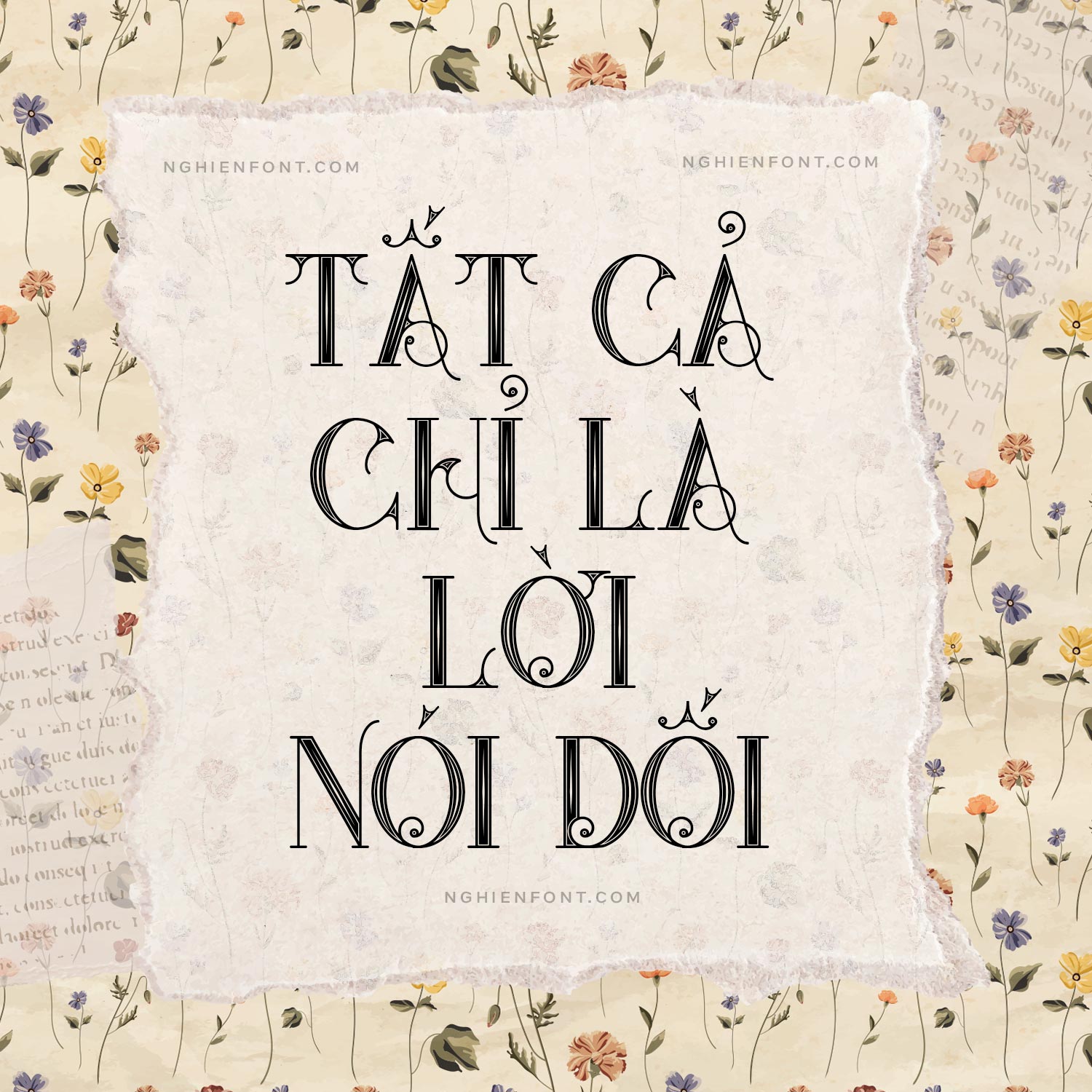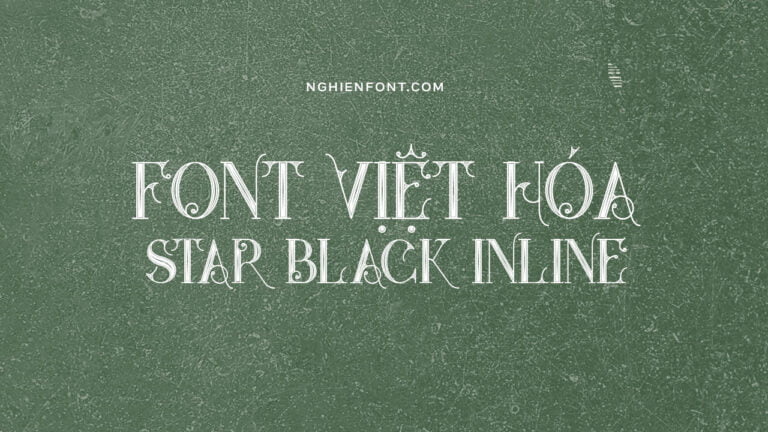
Font việt hóa LNTH Star Black Inline là kiểu chữ hiển thị độc đáo có dấu câu, chữ ghép, nét tượng hình và chữ cái được thiết kế bởi Jumbo Design.
Kiểu chữ này được lấy cảm hứng từ những thiết kế bìa album, đĩa nhạc, áp phích của thập niên 70, các nét vẽ cổ và khả năng trang trí đẹp mắt mang đến cho 1 kiểu chữ vô cùng nổi bật và ấn tượng.
Đội ngũ tại xưởng đúc monotype đã phát hành một bản cải tiến của phông chữ truyền thống cổ xưa, bây giờ gọi là Star Black Inline. Không có bất kỳ giới hạn nào liên quan đến thiết kế banner ngoài ý tưởng và sự sáng tạo của riêng bạn.
Star Black Inline đẹp mắt và sang trọng này phù hợp để sử dụng cho các thiết kế như tiêu đề, trích dẫn, dự án, thiệp mời hoặc cần một kiểu chữ hiển thị đẹp mắt và nổi bật.